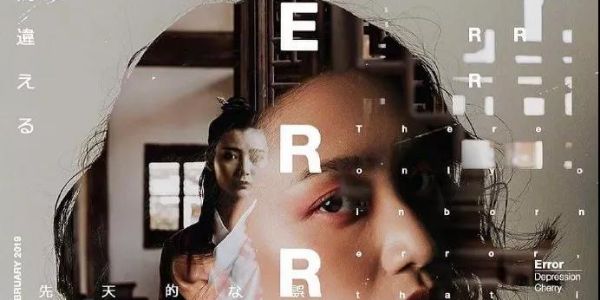
玩转版式设计的点、线、面!版式设计教程。
在版面编排中,点、线、面既是最基本的造型元素,又是最重要的表现手段。版面编排中的文字与图形都可以理解为点、线、面(形状)的集合。
在版面中的点的聚集力可以表现为文本与图形的始与终,点运用对齐的原则与线呼应,运用扩张的原则与面呼应,版面中的这种点线面的转换,形成了点的聚焦、线的对齐、面的扩张,从而激活版面空间。可以说二维的平面设计,就是点线面的游戏。
①在平面世界点是造型语言的出发点,点又是灵活多变的,点可以包罗万象。点具有可吸引观众的注意力的焦点的作用,点在向内聚焦的同时又向外辐射。点在版面中看起来是简单的图形,但它又是复杂的,是其它所有图形构成的基础。
②线的特征是浪漫,线的表现可以是表象的、也可以是隐含的;线可以是动态的、也可以是静止的;线可以分割空间,可以连接空间,还可以包围和约束空间。
直线是线中最简洁明快的形态,直线又分水平线和垂直线,水平线使人联想到宽广的地平线,垂直线可以让人感觉到高度与深度;曲线有优美感和动感;而折线则有紧张感、尖锐感。线的形态之中又有粗细浓淡之分,粗线有力又醒目、细线纤细又锐利,粗线有前进感,细线则有后退感。
③面是点的放大,线的聚集。面具有一定的面积和质量,占据的空间和位置更多,面的视觉冲击力更大、更强烈。在版面中,面给人以整体美感,使空间层次丰富,使单一的版面多样化。面通过外轮廓形来影响版面,尤其当外轮廓形复杂时,形成一种丰富而活跃的视觉效果。
文字以点的形式,作为版面最基本的视觉元素,在整个平面设计中占有重要的份量。文字这种信息材料不仅可以提供读者最直接的文字魅力,还能提供读者具有迷惑力的视觉效果。文字点的聚集,形成版面独具特色的文字肌理。文字肌理在疏密、粗细、线性、聚散、韵律上发生着丰富多彩的变化。这种变化的文字肌理群交错在版面中形成令人玩味的点的世界。
文字群的聚与散、疏与密,是分清层次关系的重要手段,还是解决版面创新的重要途径。在连续的密集的文字群中,改变某个或某些文字的大小、字重或字体,以及空间位置,都可以创造出一种奇特的、令人赏心的版面空间。
版面中的文字排成行形成线的形状,无数条对齐的字行聚在一起组成栏。文字的对齐与分栏在版面编排中,形成的线与面的交替。线本身在视觉上就与字体的线条类似,而对比关系,包括粗细、软硬、长短等,在线条之间或字体的线条之间发挥着一样的作用。字里行间的水平线和垂直线在视觉上与文本的内在特征相对应。版式上的角状线、曲线或波状线与文本的逻辑形成和谐与对比。
文字的排列由点到线,由线到面,它的内部空间往往是点线的规划。而面则赋予了它可变性、灵活性、转换性,使之产生了不同形态、不同性格、不同特征。对于面的不同分割、不同位置的变化,还能营造出丰富的版面空间层次。
图像在版面空间中,不管是点汇集的图像,还是线汇集的图像、面汇集的图像,都因为他们各自的内在含义,以及外在形态,产生各不相同的版面视觉效果。一幅图像可以非常写实的绘画,也可以非常抽象的点线面构成,还可以是写实向抽象的过渡,不管怎样它都必须是包涵丰富内涵的信息传递符号。
写实的图像、抽象的图像、写实与抽象参半的图像,归根到底都是由点线面汇集的图像。图像中点线面的运用是惟妙惟肖的,它既能表现生动的写实形象,更能表现夸张的概括形象。单纯的点制作的图像、单纯的线制作的图像、单纯的面制作的图像,都会给人以视觉的纯粹感、给人以视觉的冲击力。
而点线面共同制作的图像,将点线面各自的特点表现到极致,同时更重要的是点线面能将图像所要表现的意义精准而到位的表现出来。这样的点线面运用于图像中才会最生动、最有意义。推荐阅读:版式设计中的"隐藏力量"!留白
在版面空间中,无论文字、图形、空白等多么复杂,最终都可以归纳到点线面上来解决。以点定位、以线分割、以面格局,从而构成了完整的版面。形形色色的点线面,形形色色的文字组合和图像模式,都要做到合适的版面空间。当点线面之间建立起清晰的关系,各式各样的设计方案就会从头脑中涌现。
①在版面中的点,可以是文字,也可以是图形,更可以是视觉焦点的那个点。而作为视觉焦点的点,一定是版面的第一信息传达点。由于视觉焦点的大小、形态、位置的不同,所产生的视觉效果和心理作用也不同。在版面设计过程中,将视觉焦点置于视觉中心,是常见的手法,比如:将行首字放大起着引导、强调、活泼版面和成为视觉焦点的作用。
当视觉焦点居于版面中心时,上下左右空间对称视觉张力均等,即给版面以庄重感。当视觉焦点在版面偏左或偏右,产生向心移动趋势,使版面具有动感。现在,为了追求新颖的版面,更多地将视觉焦点向左、右、上、下边置。准确运用版面中的各级视觉焦点是版式设计追求的更高境界。
②版面编排中常用的网格编排法,就是用线建立多个相同的等量分割空间在分割的网格内进行版面编排,以获得秩序与美。线是版面中网格编排的骨架,网格中的线既要考虑各元素彼此间的对齐与呼应,又要注意各分隔空间的内在联系。保证良好的空间秩序感,就必须做到被划分的网格空间有相应的主次关系,以此形成整体和谐的版面效果。
③版面中的面多是较抽象的概念,没有具体的形,主要是由文字或图形集成的块面。这些块面在版面中具有平衡层次、丰富空间的作用。版面编排时,将文字、图像集成合适的块面,置于版面上、下、左、右的空间位置中,依据视觉流程线,将重要的信息点安排在版面第一视觉中心,其他信息则依次放在版面的次级空间,在分割好的块面里,建立疏密有致的位置关系,使产生的空间层次赋有创意。
①在版面编排中,点线面常常还以纯粹几何形态出现,其本身不代表任何意义,通过比较、互衬、格局、运动等丰富版面空间。在版面上,大小不等的几何点以及群化的密集点,能给人带来点的视觉浪潮。在版面中等间隔的点的排列,会使观众感受到严紧、规律、秩序之美;而自由散漫的点排列,使版面轻松、活泼,具有浪漫之美。
②抽象的线在版面具有极大的灵活性,它可以任意变换方向、形态。不同组织的几何线会产生出不同的节奏、韵律以及层次感。线在版面的表现力极为丰富,能诱导出无限的版面空间。线在版面中的装饰作用,具有动感、方向感、韵律感。这种线在版面能起到很强的活跃气氛的作用。
③抽象的块面在版面编排中常常配以色彩,形成漂亮的色块,应用于版面的底色编排中。在版面上,大面积的色块,能烘托出各种各样的氛围,视觉效果最为显著。点线面以含蓄、理智、条理、丰富的意境引起人们的情感共鸣,它们为平面设计带来了无限的创意空间。